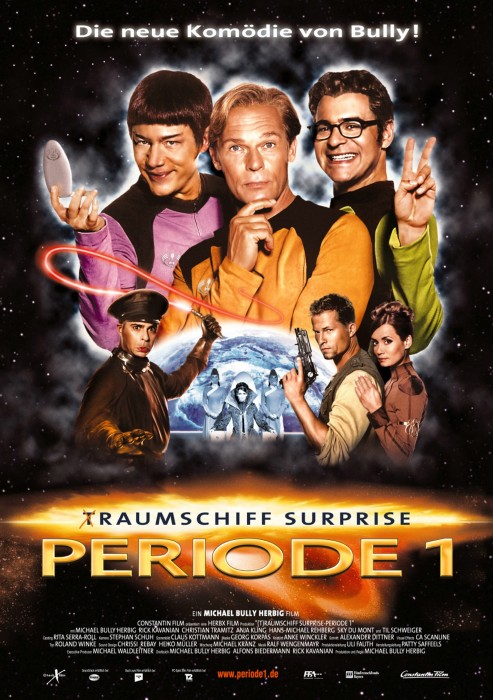
(T)Raumschiff Surprise
Suche für meine dvd Sammlung die passenden Fonts
Fange mit dem hier an
Bei den ersten beiden Zeilen würde ich eine böse verzerrte TheSans vermuten. Aua! Auch die Credits könnten damit gesetzt worden sein …